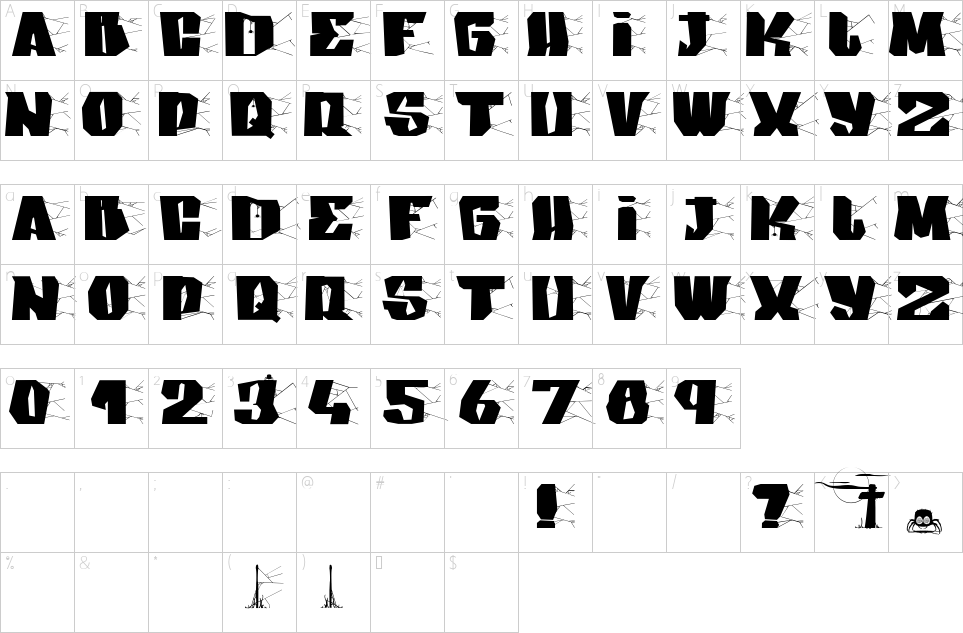
A fonte Arakphobia é uma opção gratuita e única para designers e criadores de conteúdo. Desenvolvida pela designer Maelle Keita, ela tem sido baixada por mais de 19.835 pessoas. Arakphobia oferece uma combinação única de linhas modernas e linhas leves, ideal para criar texturas e gráficos em alta qualidade. Este é um recurso adicional valioso para aqueles que estão sempre em busca de fontes de alta qualidade, mas desejam manter seus orçamentos sob controle. A Arakphobia font se destaca por seu desenho elegante e claramente personalizado, tornando-a uma escolha ótima para um catálogo de recursos gráficos gratuito. Seja você um designer web, um ilustrador ou até mesmo um criador de conteúdo digital, Arakphobia oferece um conjunto de ferramentas que irá aprimorar seu trabalho.